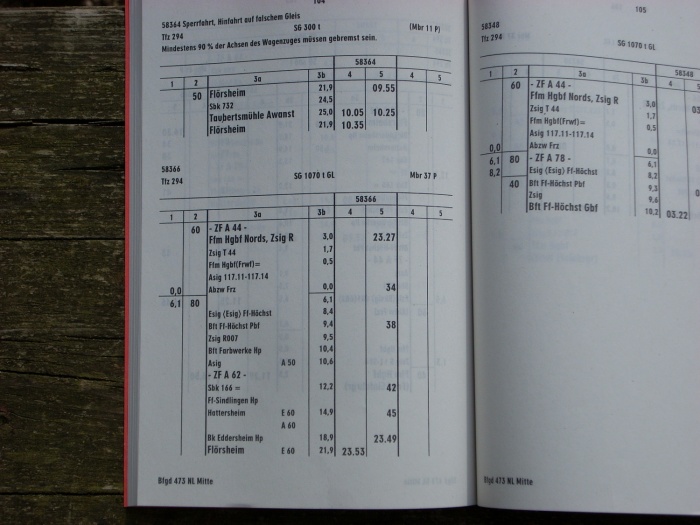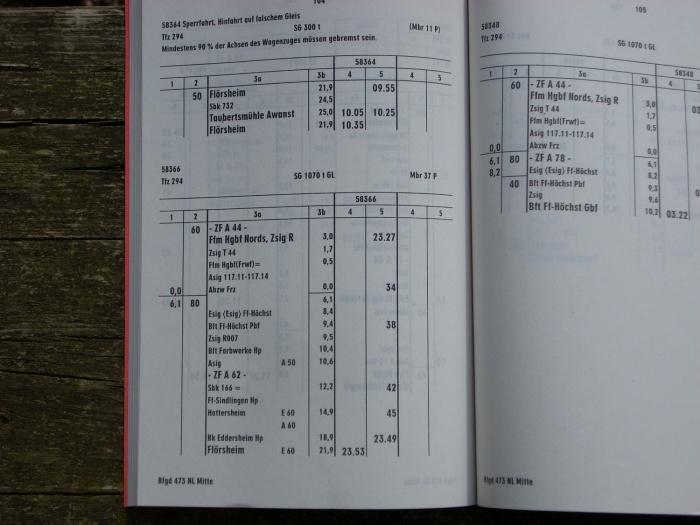
Eine "altmodische" Druckschrift wird gesucht
wie man an meinem Nick "Zwiebelfisch" bereits erkennt, gehöre ich fachlich gesehen eigentlich ebensowenig hierher wie eine Arial-Letter in den Times-Setzkasten - ich habe nichts mit Typographie im weitesten Sinne zu tun, außer daß ich sehr regelmäßig viele Buchstaben lese. Dieses Forum fand ich bei der Internetsuche.
Ich erbitte von Euch eine Auskunft über eine alte Schriftart:
mir kam ein Dienstheft der Bundesbahn in die Finger, in dem eine herrlich "altmodische" Schriftart verwendet wurde. Irgendwie habe ich das Gefühl, es wäre noch richtiger Bleisatz. Vor allem die spitzwinkelige Ziffer "3" empfinde ich als 60er-Jahre-Stil.
Kennt jemand diese Schrift, und kann man sie als .ttf-Datei downloaden?
Wichtig ist noch, es muß nicht mit aller Gewalt die bahnamtlich-originale Schrift sein, ich bin auch mit einer weitestgehend ähnlich aussehenden zufrieden.
Der Hintergrund: ich möchte jemandem, der in den Ruhestand geht, zum Abschied ein "alt" aussehendes "Dokument" erstellen.
Ich bin wirklich beeindruckt vom Fachwissen der Leute, die nach kurzem Betrachten eine Schrift identifizieren können.
In der Tat ist Dein erster Vorschlag passend, diese Schrift wäre sehr gut. Leider ist sie kostenpflichtig. Gibt es eine Free-Font-Alternative?
Aber es war kein Problem, eine Alternative zu finden. Die Welt ist eine Guugel:
Du hast nicht zufällig eine Futura Condensed auf Deinem Rechner? Für Deine Zwecke täten es sonst sicher auch die legitim kostenfreien Serifenlosen Oswald, Archivo oder Roboto bei fontsquirrel.
Thierry hat aber die authentischsten rausgesucht. Alles andere sind eher Kompromisse des Geldes wegen. ;-)
Danke schön für Deine Auskünfte und Hinweise. Ich bin inzwischen auch fündig geworden.
Die vorschnell heruntergeladene Raubkopie erwies sich übrigens als echter Rohrkrepierer: tippen konnte ich zwar wie ein Weltmeister, aber ausdrucken - Fehlanzeige! Absturz des Druckauftrages und Fehlermeldung der Textverarbeitung. Daraus habe ich gelernt: ich werde nicht nocheinmal etwas blauäugig installieren.
die Neuzeit Grotesk findet man als Geometric 706 in den Bitstreamschriften die Corel mit einigen Produkten, wie Corel Draw, mitliefert. Alte Versionen von Corel Draw sind für wenige Euro bis geschenkt erhältlich. Mit der Übergabe des Datenträgers gehen auch die Rechte an den rechtmäßigen Besitzer des Datenträgers über. So bin ich an meine Geometric 706 gekommen.
Es gab vor vielen Jahren mal eine Schrift mit Namen Geometrix in den Schnitten Regular und Black, welche auch eine Neuzeit Grotesk ist. Die Schrift wurde als Freeware deklariert ... wobei ich da aber keine Garantien geben würde. Man findet die Geometrix jedoch in den obskuren Schriftseiten.